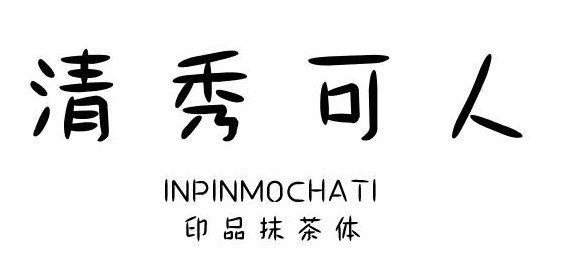
印品抹茶字體是義啟字庫推出的印品系列字體,字跡結(jié)構(gòu)和諧,一筆一劃很有美感,讓文字更加生動娟秀,給人抹茶般的香甜潤滑感,綠色資源網(wǎng)今日推薦!
“碧云引風吹不斷,白花浮光凝碗面”抹茶字體一筆一劃飄逸瀟灑,仿佛由無數(shù)片嫩葉組合而成,給人生機勃勃的感覺,愿為你帶去一絲微甜。
印品系列字體與常規(guī)的手寫體不一樣,擺脫了隨心隨性的設計理念,更注重字體的形態(tài)和結(jié)構(gòu),讓大家更容易接受,在視覺上也有著不錯的美感,運用在平面設計、海報設計、包裝設計等行業(yè)均有不錯的效果。